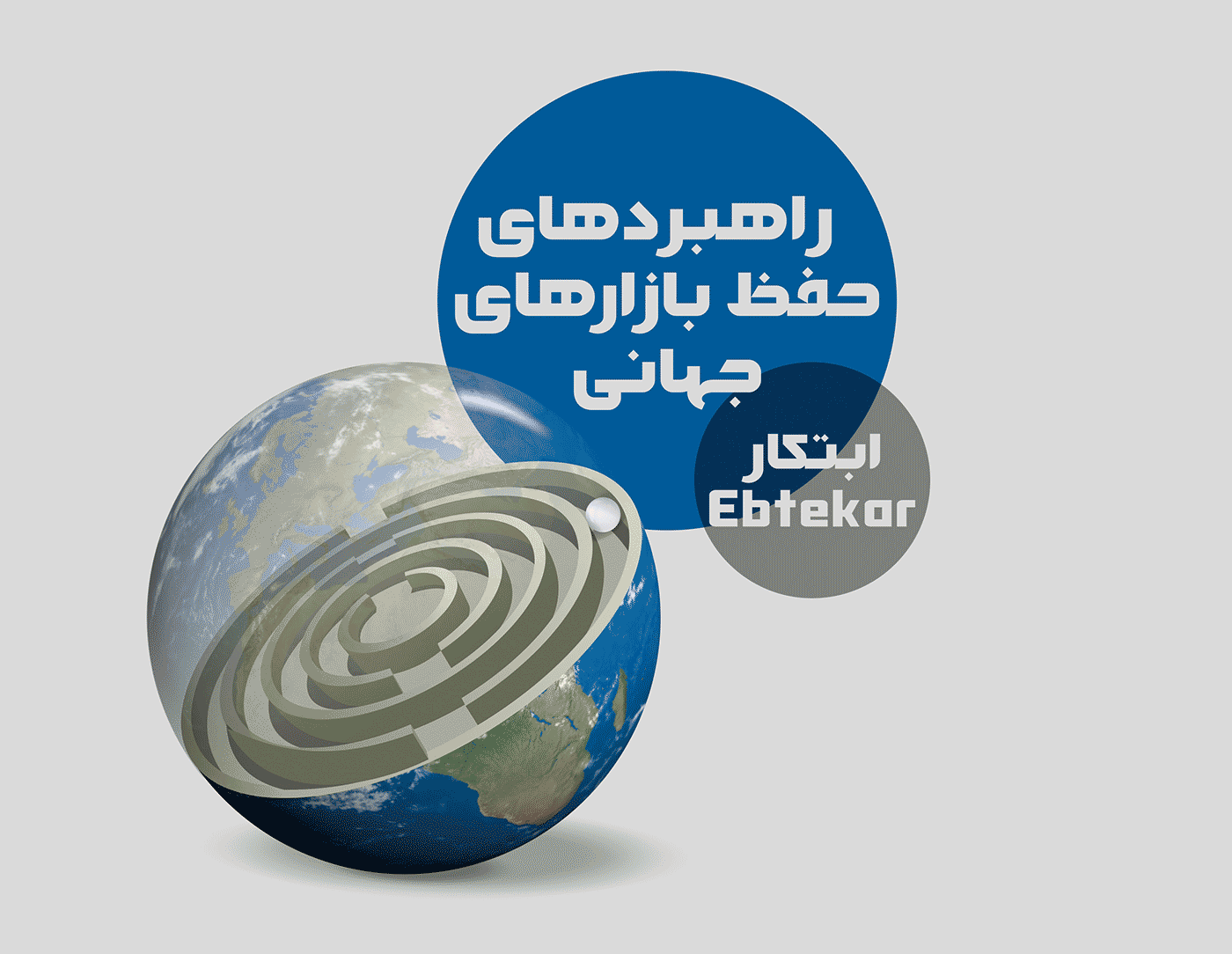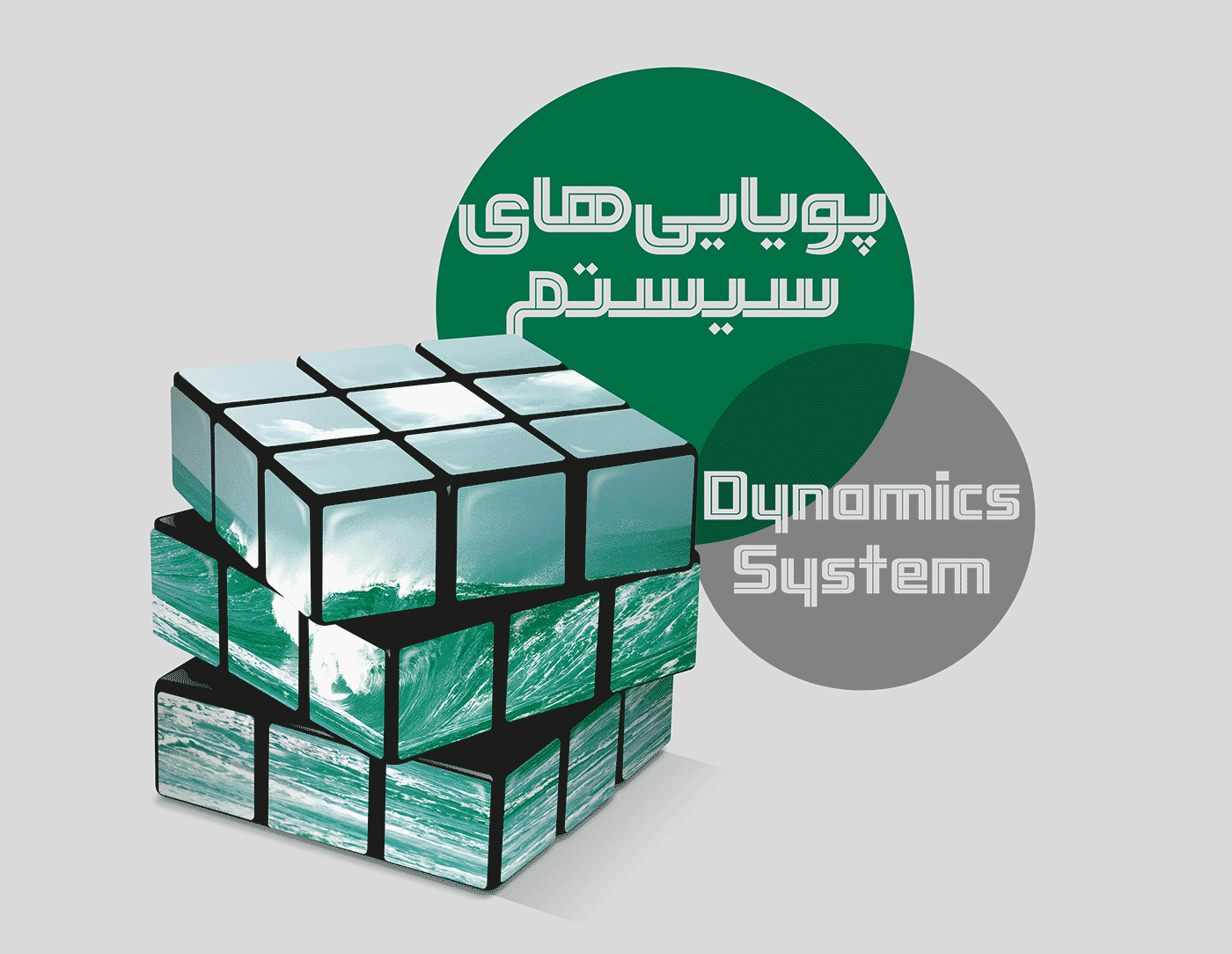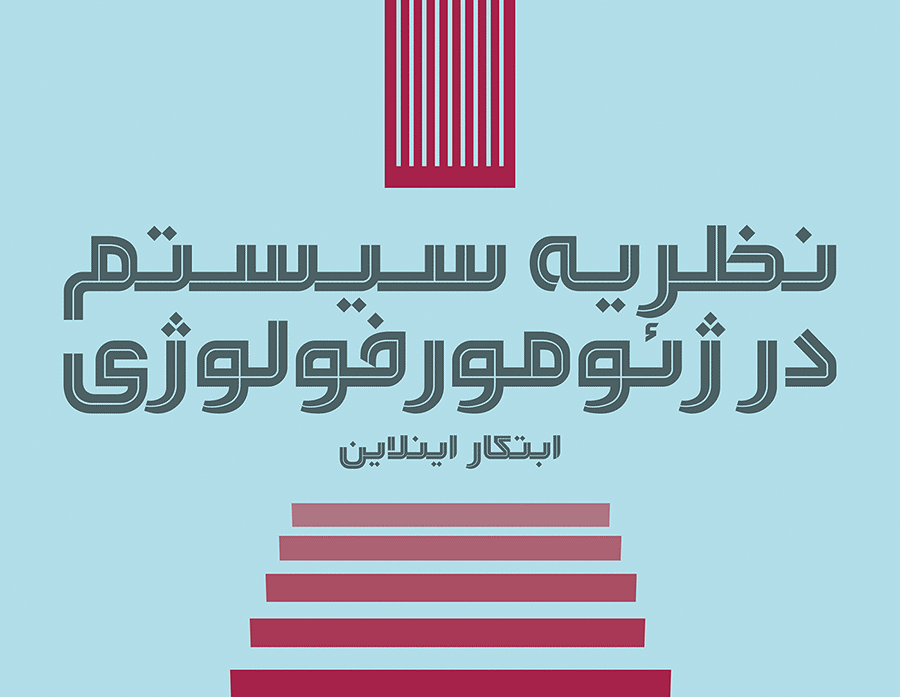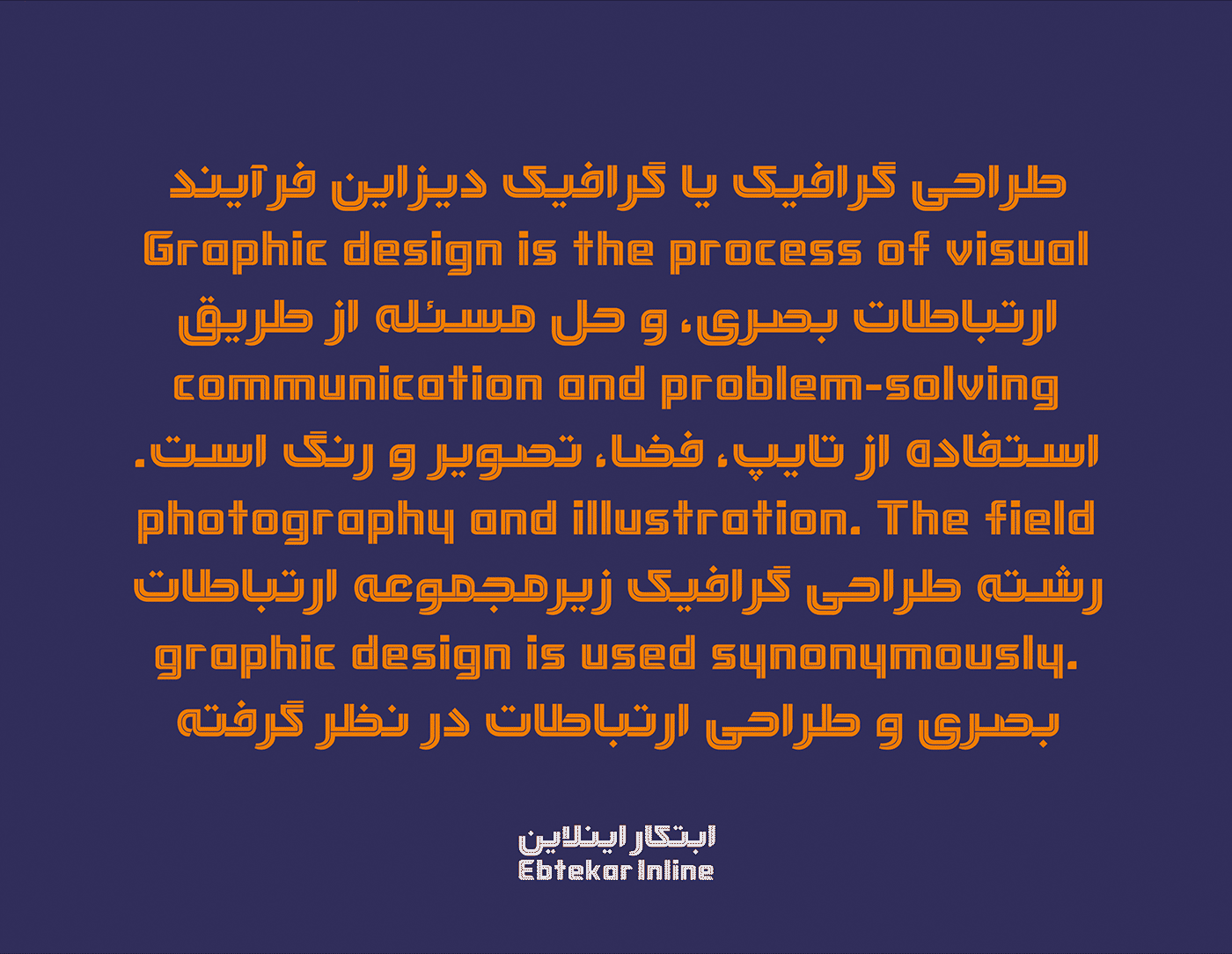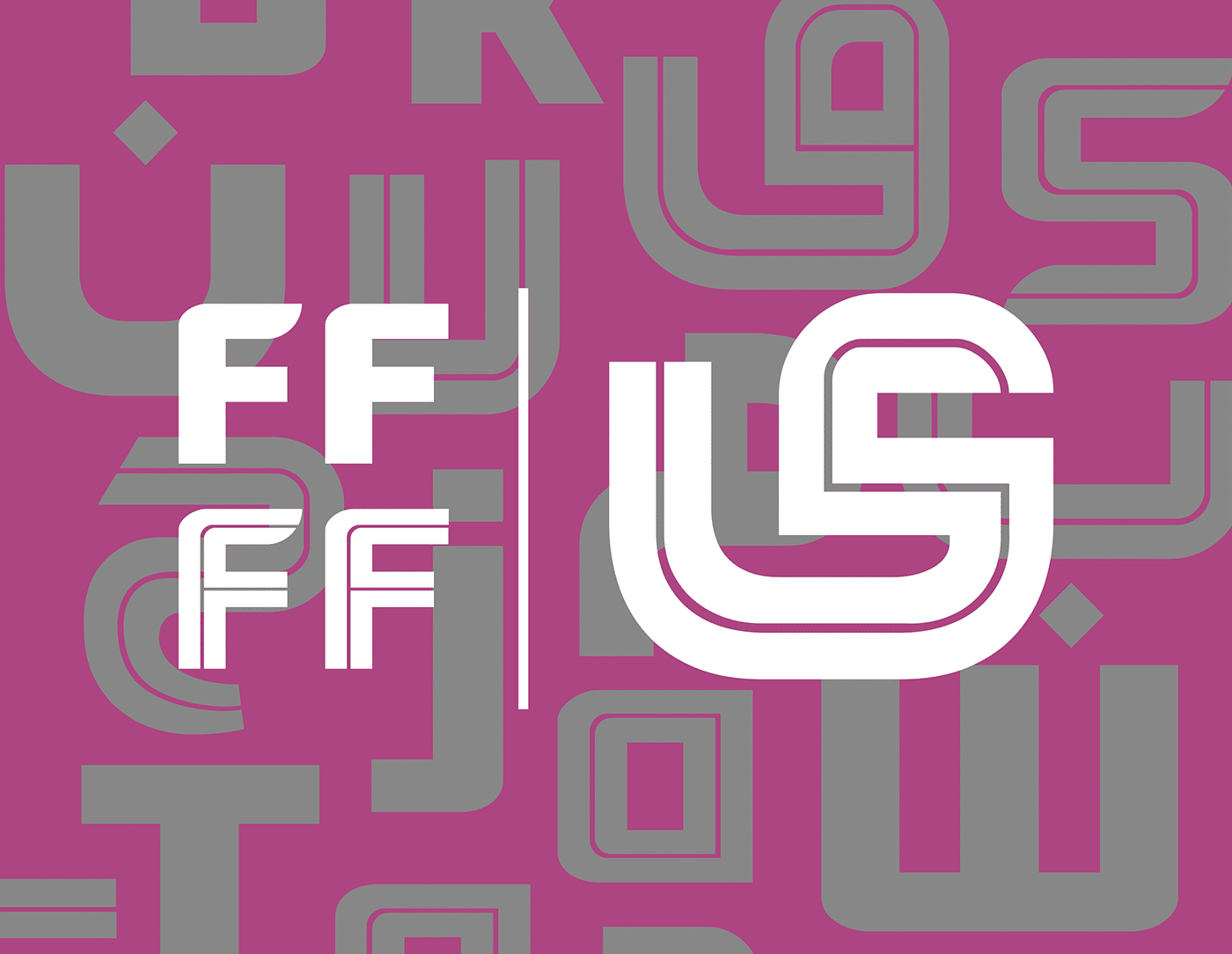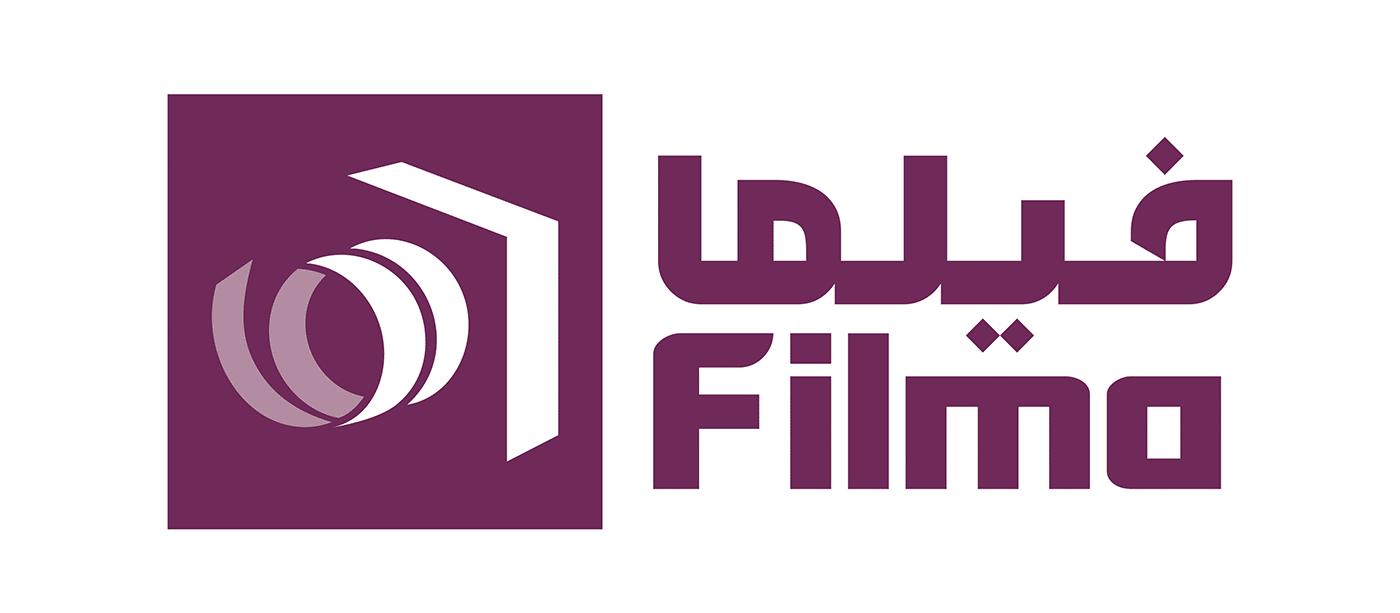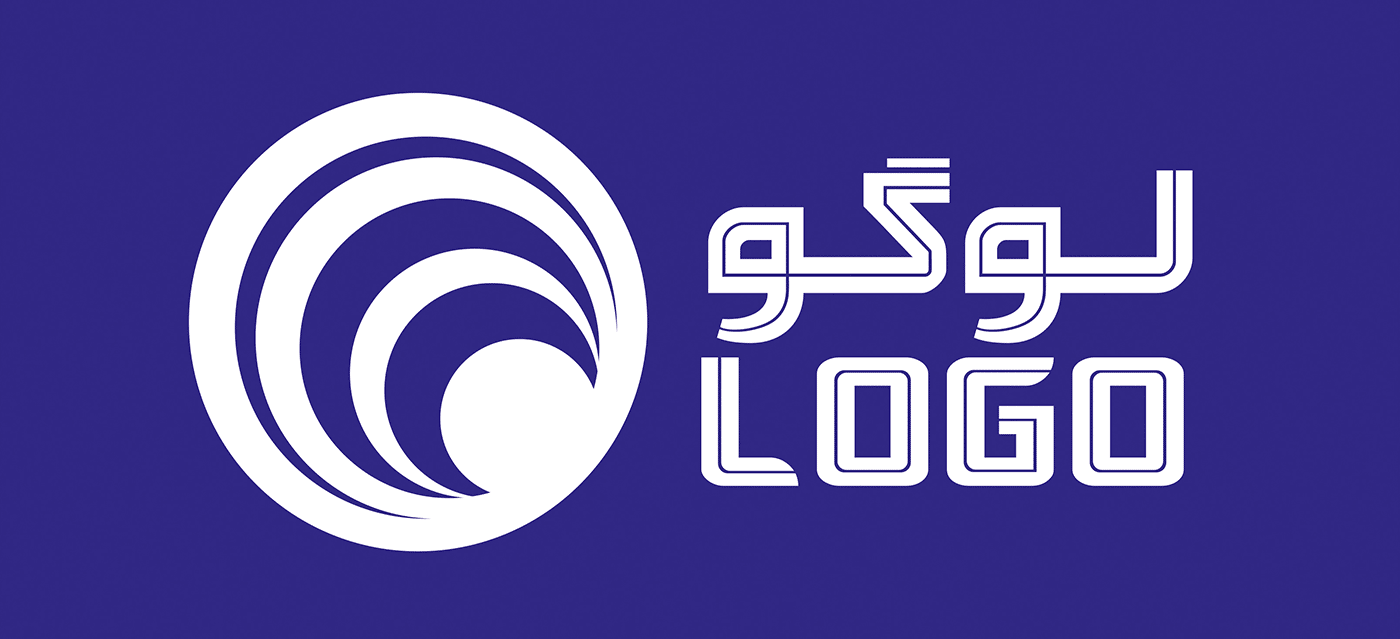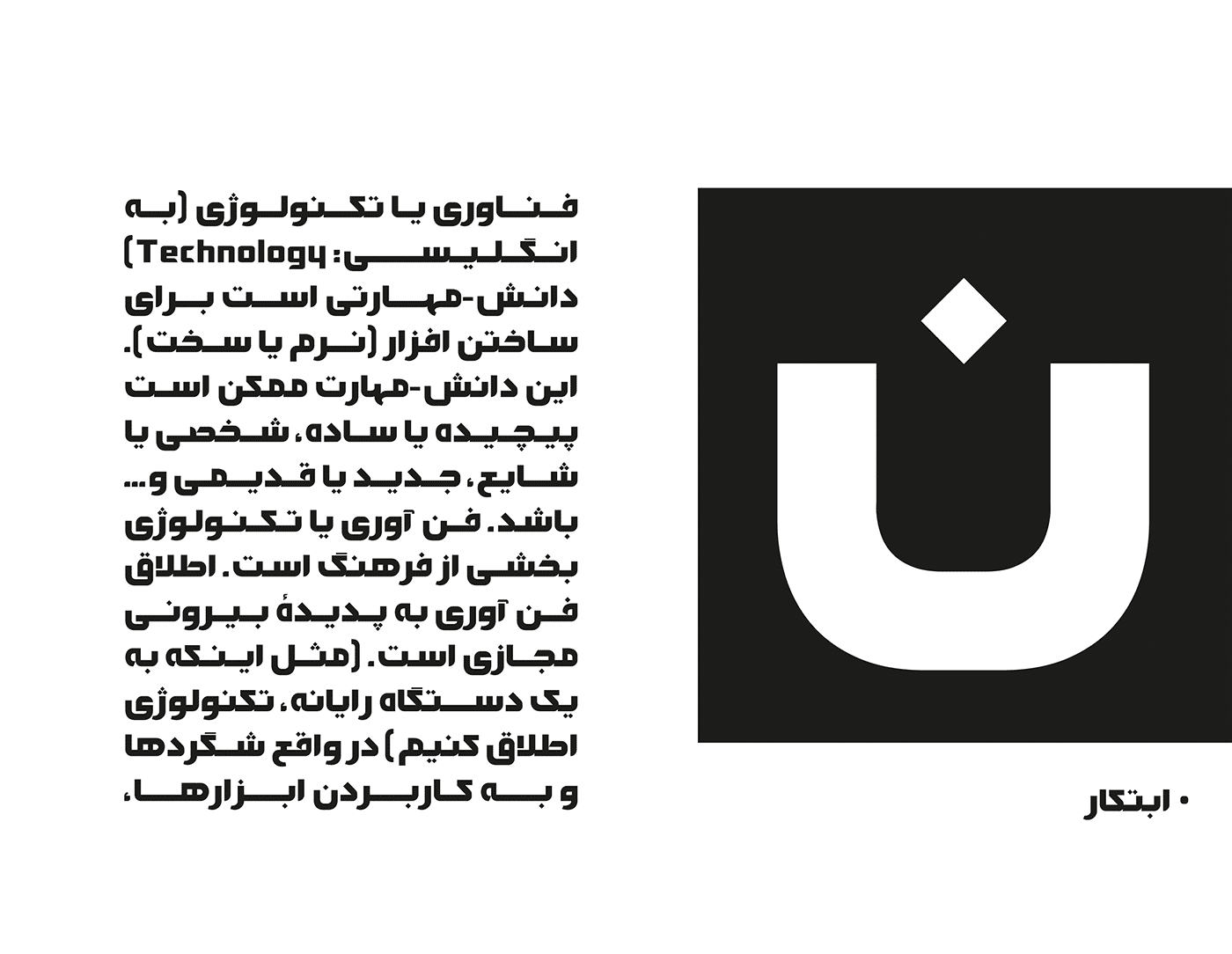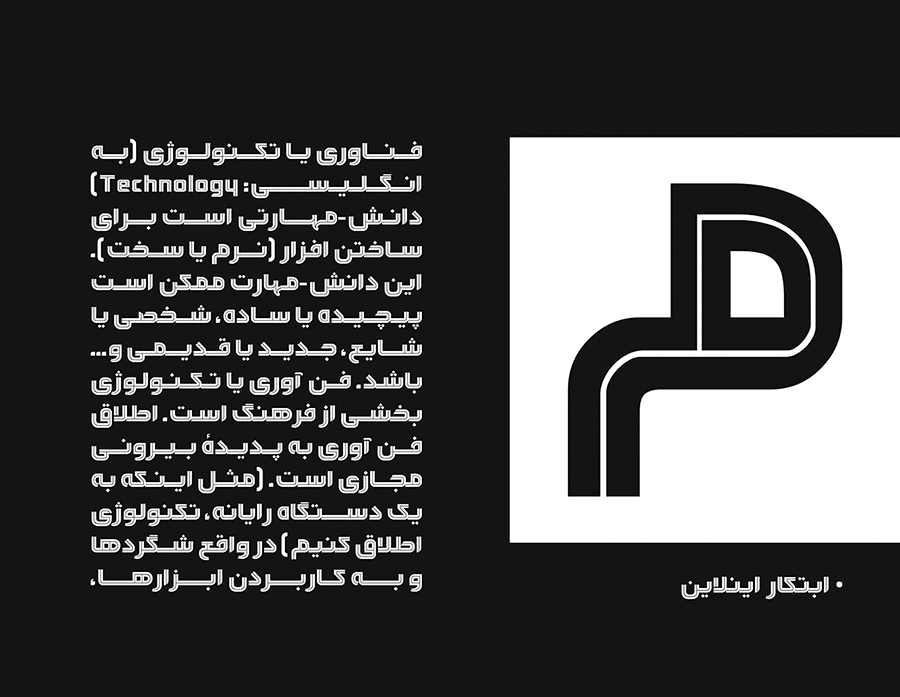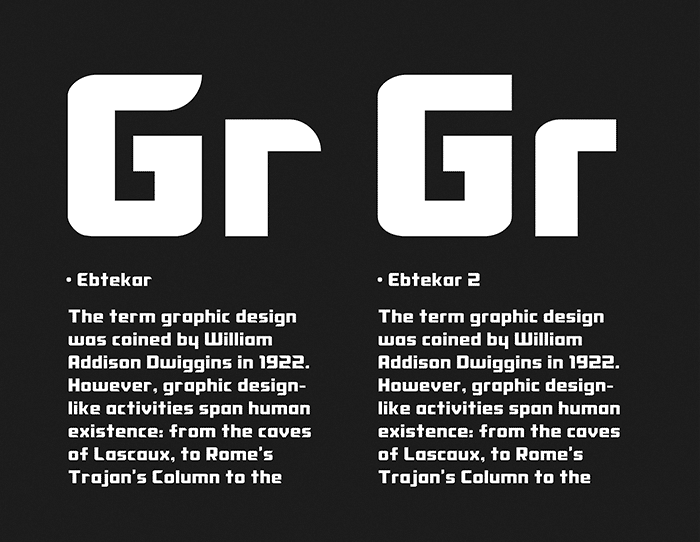
فونت ابتکار در پنج زبان لاتین، عربی، فارسی، پشتو و اردو قابل استفاده است.
این قلم دو حالت متفاوت دارد؛ معمولی و اینلاین. که البته در حالت لاتین دو سبک متفاوت وجود دارد که با نامهای Ebtekar 2 و Ebtekar_inline2 آنها را دریافت میکنید.
قلم ابتکار در نخستین سالانۀ هنر طراحی کتاب در سال ۹۴ شایستۀ تقدیر شناخته شد.
قلم ابتکار انتخاب مناسبی برای طراحی سریع لوگوهای ۲زبانه است.
قلم ابتکار ساده (Ebtekar)
فونت ابتکار اینلاین (Ebtekar inline)
تفاوت حروف لاتین در فونت ابتکار ۱ و ۲
تفاوت حروف لاتین در فونت ابتکار اینلاین ۱ و ۲